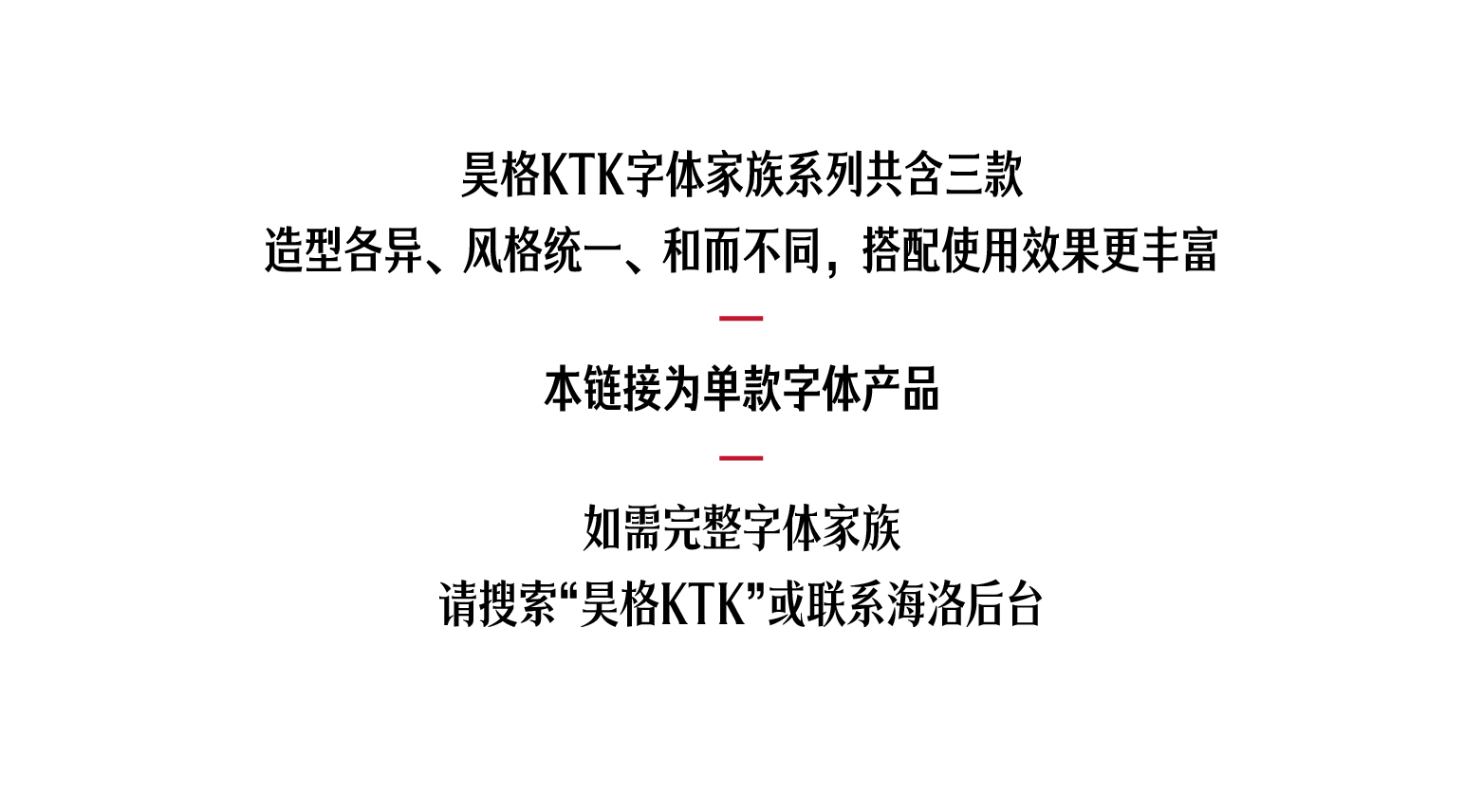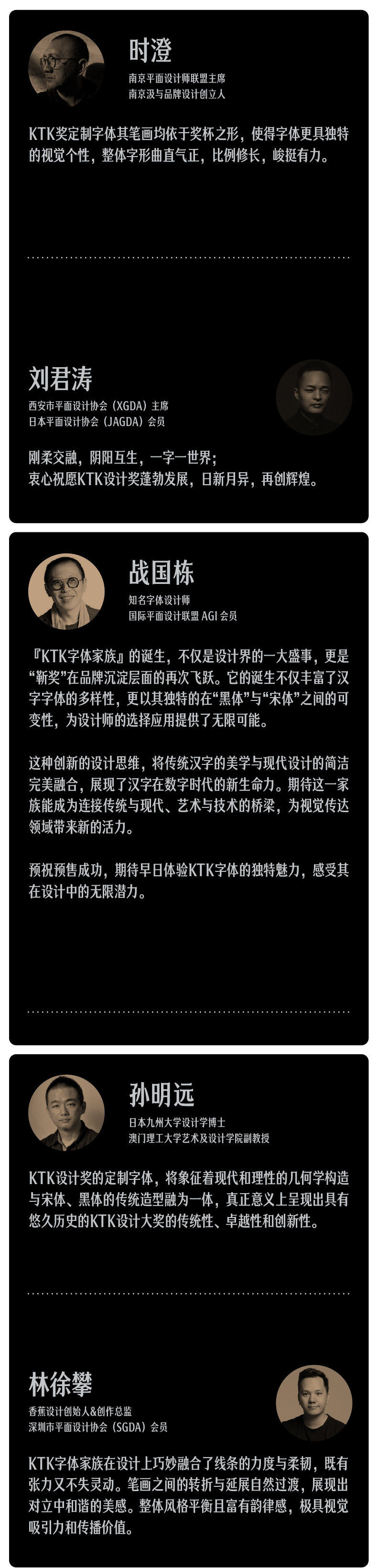
昊格KTK家族 A
昊格KTK家族 A,KTK字体家族以“传承创新”的精神为核心,结合“创意独特”与“面向未来”的设计理念。字体设计注重字面窄幅与重心上移,突出横竖对比和系统的可变性,旨在为现代视觉传达提供独特的文字表达形式。该字体家族构成:A款字体:灵感源自KTK奖杯的正面和底面,考虑到侧面视角,融合时尚黑体与几何美学,表现文化的交融。C款字体:受奖杯侧面和顶面启发,同时融合正面元素,结合人文宋体与几何美学,展现深厚的文化融合。B款字体:由A款与C款的差值创造,类似奖杯的中间过渡方案,展现刚柔并济的设计风格,曲直与阴阳的完美结合。该字体家族展示了从无衬线到衬线的流变,体现了现代与传统的交融,以及几何与文字的对话。设计中体现极致工艺,彰显“传承创新”的品牌理念和奖杯造型的刚柔并济。字体采用兼容并蓄的设计哲学,反映人文精神与科技的融合。字体方案中拓展了横笔画的粗细变化,以优化视觉效果和增强可读性。设计保持与原版的比例一致,承袭熟悉的视觉感受,同时在简约中寻求变化,增添时尚与人文的深度。该字体家族不仅增强了与奖杯的视觉联想,还通过粗细对比的优化提升了整体的可读性。该字体家族以其木器感和挺拔的形态,既展示了设计的独创性,也符合现代审美的需求。商业用途